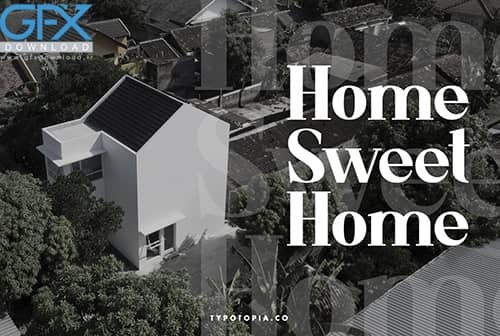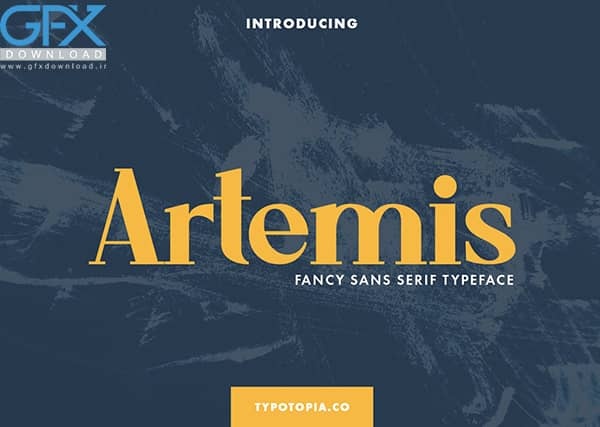
دانلود فونت انگلیسی Artemis Fancy
دانلود فونت انگلیسی رایگان Artemis Fancy
دانلود رایگان فونت انگلیسی آرتمیس Artemis Fancy
یک فونت فوق العاده منحصر به فرد و جالب برای طراحی های شما است که برای پروژه خلاق بعدی شما مانند لوگو ، قیمت چاپ شده ، دعوت نامه ، کارت ، بسته بندی محصول ، عنوان ، لوگو تایپوگرافی ، سربرگ ، پوستر ، طراحی لباس ، برچسب و غیره کاملاً مناسب است. این فونت همه کاره همچنین از کاراکتر های چند زبانه پشتیبانی می کند. استفاده از آن بسیار سرگرم کننده است زیرا هر کلمه می تواند به دلخواه شما تبدیل شود. برای دانلود فونت انگلیسی Artemis Fancy از جی اف ایکس دانلود به ادامه مطلب مراجعه کنید.
فونت انگلیسی Artemis Fancy
• حروف بزرگ و کوچک
• شماره گذاری و علائم نگارشی
• پشتیبانی چند زبانه